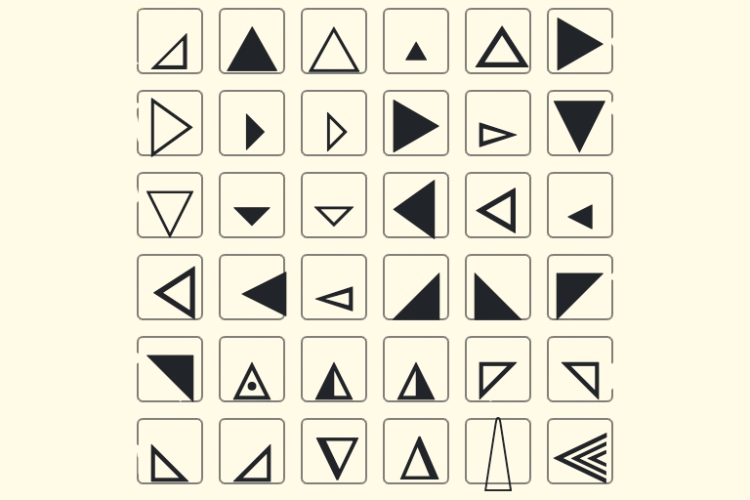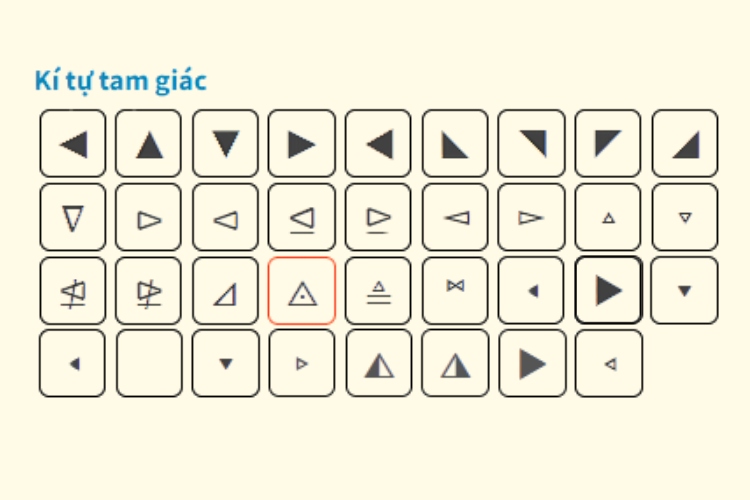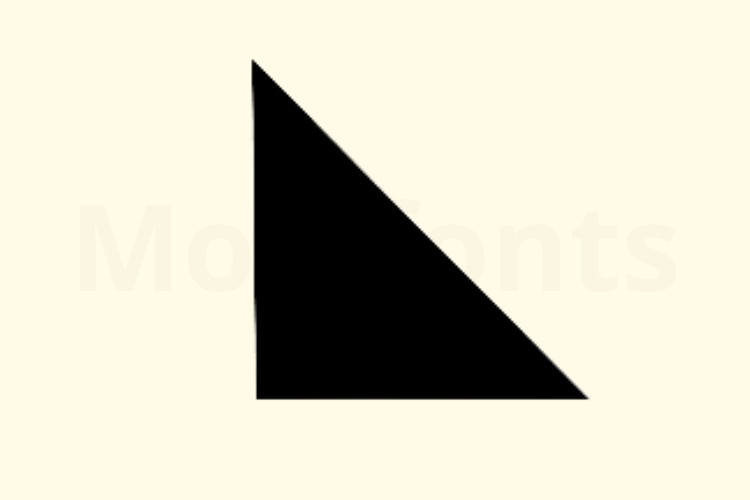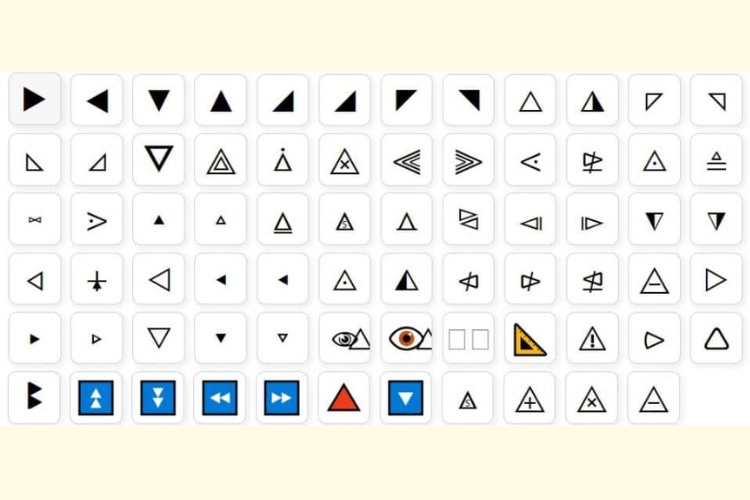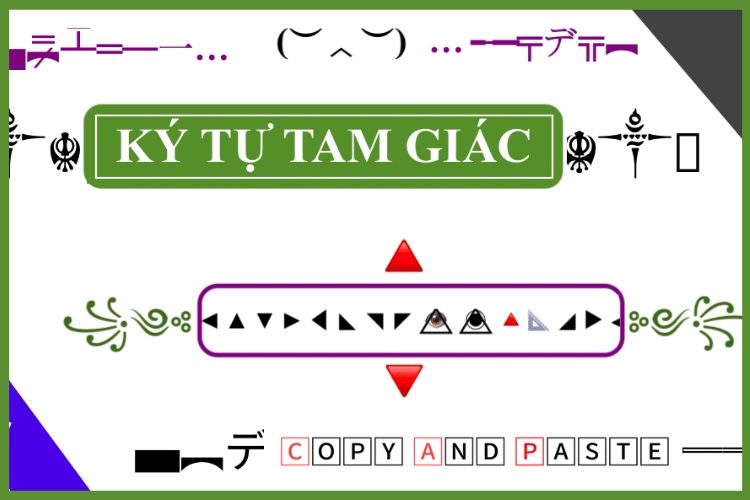
Bạn đang tìm kiếm những kí hiệu tam giác độc đáo, dễ dùng và tương thích trên mọi nền tảng? Kí hiệu tam giác là một lựa chọn hoàn hảo, phù hợp để tạo dấu ấn cá nhân trong tên game, bio TikTok hoặc bài đăng Facebook.
Bộ sưu tập các icon tam giác gồm cơ bản và hướng lên, hướng xuống, bên trái và phải, icon tam giác đặc biệt và phá cách, màu sắc, tên game ấn tượng, kiểu chữ sáng tạo dưới đây giúp bạn dễ dàng sao chép và sử dụng.
Kí hiệu tam giác là các biểu tượng dạng hình học với ba cạnh, thường dùng để thể hiện hướng, phân tách nội dung hoặc tạo điểm nhấn thẩm mỹ. Nhóm biểu tượng này được nhiều người dùng tìm kiếm vì mục đích thiết kế tên game, tiểu sử mạng xã hội hay bài viết cần sự sáng tạo.
Các ký hiệu tam giác biểu thị sự chuyển động, chỉ hướng, hoặc đơn giản là tạo ra một hiệu ứng hình ảnh nổi bật khi kết hợp cùng các kí tự khác như kí tự hình tròn, ngôi sao, biểu tượng cảm xúc,…
Dưới đây là bảng tổng hợp đầy đủ các kí tự đặc biệt tam giác dựa theo các nhóm: cơ bản và hướng lên, hướng xuống, bên trái và phải, icon tam giác đặc biệt và phá cách, màu sắc, tên game ấn tượng, kiểu chữ sáng tạo:
Kí hiệu tam giác cơ bản và hướng lên dùng để tạo cảm giác tích cực, nổi bật. Theo Unicode Consortium, các biểu tượng này nằm trong khối Geometric Shapes (U+25A0 – U+25FF). Dưới đây là bảng tổng hợp chi tiết các kí hiệu tam giác cơ bản và hướng lên:
Biểu tượng |
Tên Unicode |
Mã Unicode |
Mô tả ngắn |
▲ |
Black Up-Pointing Triangle |
U+25B2 |
Tam giác đen hướng lên |
△ |
White Up-Pointing Triangle |
U+25B3 |
Tam giác trắng hướng lên |
▴ |
Black Up-Pointing Small Triangle |
U+25B4 |
Tam giác đen nhỏ hướng lên |
▵ |
White Up-Pointing Small Triangle |
U+25B5 |
Tam giác trắng nhỏ hướng lên |
◬ |
Up-Pointing Triangle with Dot |
U+25EC |
Tam giác hướng lên có dấu chấm ở giữa |
◭ |
White Up-Pointing Triangle with Dot |
U+25ED |
Tam giác trắng hướng lên có dấu chấm bên trong |
◮ |
Up-Pointing Triangle with Left Half Black |
U+25EE |
Tam giác hướng lên, nửa trái tô đen |
Các ký hiệu tam giác hướng xuống thường dùng để biểu thị chiều đi xuống, lựa chọn mở rộng hoặc điểm nhấn cuối dòng. Theo Unicode Consortium, chủ yếu các biểu tượng này thuộc khối Geometric Shapes (U+25A0–U+25FF) và Mathematical Operators (U+2200–U+22FF).
Tham khảo bảng icon tam giác hướng xuống với các nội dung: biểu tượng, tên Unicode, mã Unicode, mô tả ngắn sau đây:
Biểu tượng |
Tên Unicode |
Mã Unicode |
Mô tả ngắn |
▼ |
Black Down-Pointing Triangle |
U+25BC |
Tam giác đen hướng xuống |
▽ |
White Down-Pointing Triangle |
U+25BD |
Tam giác trắng hướng xuống |
▾ |
Black Down-Pointing Small Triangle |
U+25BE |
Tam giác đen nhỏ hướng xuống |
▿ |
White Down-Pointing Small Triangle |
U+25BF |
Tam giác trắng nhỏ hướng xuống |
∇ |
Nabla |
U+2207 |
Ký hiệu đạo hàm (nabla), hình tam giác ngược |
Kí hiệu tam giác bên trái và phải dùng để chỉ hướng hoặc làm phần tử dẫn hướng trong thiết kế giao diện. Theo Unicode Consortium, tất cả các biểu tượng này đều thuộc khối Geometric Shapes (U+25A0–U+25FF).
Bảng dưới đây mô tả biểu tượng, tên Unicode, mã Unicode và mô tả ngắn của các kí tự đặc biệt tam giác bên trái và phải:
Biểu tượng |
Tên Unicode |
Mã Unicode |
Mô tả ngắn |
▶ |
Black Right-Pointing Triangle |
U+25B6 |
Tam giác đen hướng phải |
▷ |
White Right-Pointing Triangle |
U+25B7 |
Tam giác trắng hướng phải |
▸ |
Black Right-Pointing Small Triangle |
U+25B8 |
Tam giác đen nhỏ hướng phải |
▹ |
White Right-Pointing Small Triangle |
U+25B9 |
Tam giác trắng nhỏ hướng phải |
► |
Black Right-Pointing Pointer |
U+25BA |
Biểu tượng chỉ hướng phải |
▻ |
White Right-Pointing Pointer |
U+25BB |
Biểu tượng chỉ hướng phải (viền trắng) |
◀ |
Black Left-Pointing Triangle |
U+25C0 |
Tam giác đen hướng trái |
◁ |
White Left-Pointing Triangle |
U+25C1 |
Tam giác trắng hướng trái |
◂ |
Black Left-Pointing Small Triangle |
U+25C2 |
Tam giác đen nhỏ hướng trái |
◃ |
White Left-Pointing Small Triangle |
U+25C3 |
Tam giác trắng nhỏ hướng trái |
◄ |
Black Left-Pointing Pointer |
U+25C4 |
Biểu tượng chỉ hướng trái |
◅ |
White Left-Pointing Pointer |
U+25C5 |
Biểu tượng chỉ hướng trái (viền trắng) |
Icon tam giác đặc biệt và phá cách thường được dùng trong thiết kế biểu tượng, icon hoặc dấu nhấn riêng biệt. Những icon này phần lớn thuộc khối Geometric Shapes (U+25A0 – U+25FF, Miscellaneous Symbols (U+2600 – U+26FF), Miscellaneous Technical (U+2300 – U+23FF), Miscellaneous Mathematical Symbols (U+27C0 – U+27EF, U+2980 – U+29FF), Arabic Extended (U+08A0 – U+08FF).